貂明朝と源ノ明朝に見る明朝体の設計
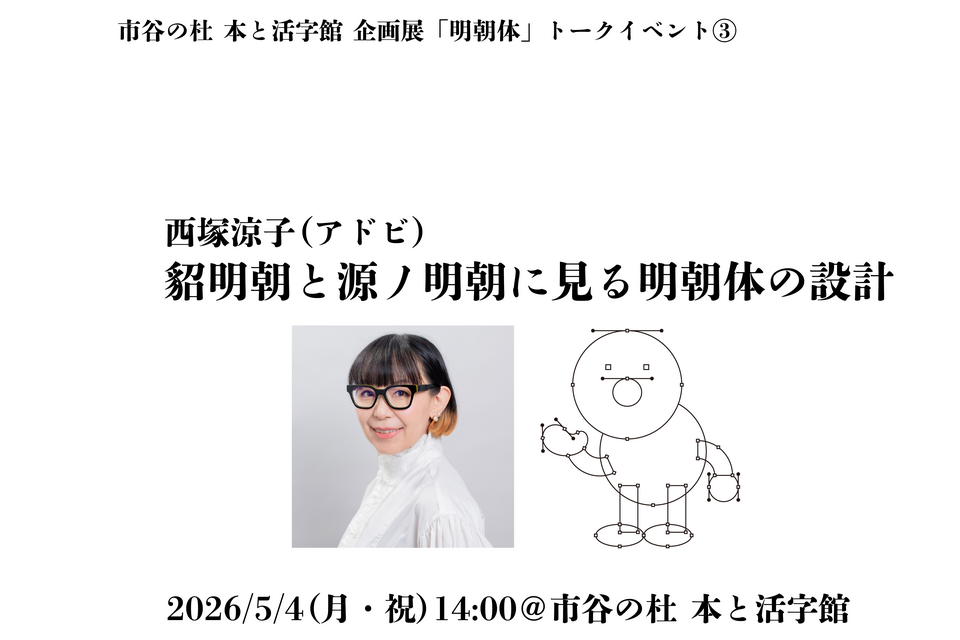
市谷の杜 本と活字館では、5/4(月・祝)に、企画展「明朝体」関連イベントとして、「貂明朝と源ノ明朝に見る明朝体の設計」と題し、アドビの西塚涼子さんに貂明朝・源ノ明朝についてお話しいただきます。
イベント名:貂明朝と源ノ明朝に見る明朝体の設計
市谷の杜 本と活字館では、企画展「明朝体」関連イベントとして、より明朝体に詳しくなり、身近に感じられるトークイベントを開催いたします。
企画展でご紹介している、明朝体史上初「かわいい」書体、貂明朝。
そして、日本語・中国語簡体字・中国語繁体字・韓国語を収録した源ノ明朝 Source Han Serif(Googleと共同開発)。
同じ2017年にリリースされた、両極端の明朝体を生み出したアドビの西塚涼子さんに、それぞれの書体の制作秘話や意外な共通点についてお話しをお聞きします。
出演:西塚涼子(アドビ)
西塚涼子
アドビ Adobe Font & Typeプリンシパルデザイナー。1995年武蔵野美術大学卒業。在学中の卒業制作が後の「かづらき」となる。1997年アドビ入社後、小塚昌彦氏のもと小塚ファミリー開発に参画。「りょう」「かづらき」「源ノ角ゴシック」「源ノ明朝」「貂明朝」などを制作。2025年に縦横比可変フォント「百千鳥」を発表。モリサワタイプデザインコンペ、NY TDC、東京TDC受賞。